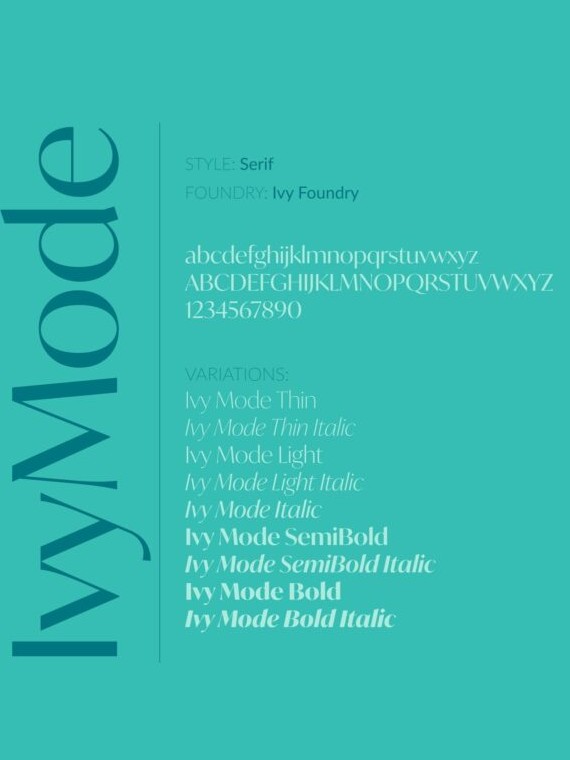
IvyMode là một bộ phông chữ thuộc dòng Sans-serif có độ tương phản cao, mang lại vẻ đẹp sang trọng, thanh lịch và đậm chất thời thượng. Với cấu trúc chữ sắc sảo và phong cách Flare Serif (những đường loe nhẹ ở đầu ký tự), việc sử dụng font IvyMode Việt hóa giúp các bản vẽ phối cảnh, hồ sơ năng lực hay bộ nhận diện thương hiệu công trình toát lên gu thẩm mỹ đẳng cấp.
Đặc điểm thẩm mỹ và phong cách của dòng font IvyMode Việt hóa
Nét lôi cuốn đặc trưng của font IvyMode nằm ở sự kết hợp tinh tế giữa tính hiện đại của phông chữ không chân và sự quý phái của các dòng Serif kinh điển. Cấu trúc ký tự sở hữu những nét thanh nét đậm rõ rệt, tạo nên nhịp điệu thị giác lôi cuốn và chiều sâu cho văn bản. Phiên bản font IvyMode Việt hóa đã được xử lý bảng mã Unicode kỹ lưỡng, đảm bảo các dấu thanh tiếng Việt được đặt ở vị trí cân đối, không làm phá vỡ cấu trúc thanh mảnh và sắc sảo của bộ chữ gốc.
Sự ổn định của bộ phông này còn thể hiện qua khả năng định hình phong cách cho các dự án kiến trúc cao cấp. Dù xuất hiện trên tiêu đề các bản thuyết minh dự án hay in ấn trên vật liệu kim loại, mica gương, IvyMode luôn duy trì được sự minh bạch và vẻ đẹp thời thượng. Đây là phương án hiệu quả để truyền tải các thông điệp về sự tinh tế, tính độc bản và tư duy thẩm mỹ nghệ thuật cho các công trình homestay, resort hay văn phòng container hiện đại.
| Phân loại phong cách | High-contrast Sans / Flare Serif / Modern |
| Mục đích phù hợp | Tiêu đề sang trọng, Logo, Profile kiến trúc |
Tư vấn trình bày: IvyMode phát huy hiệu quả thị giác cao khi bạn sử dụng cho các tiêu đề chính hoặc các đoạn trích dẫn ngắn. Do có độ tương phản nét chữ lớn, bạn nên phối hợp nó cùng một phông chữ không chân tối giản cho phần nội dung chi tiết để tạo sự cân bằng và dễ đọc cho bản thiết kế.
03 Ứng dụng phông chữ IvyMode vào thực tế công trình
Nhờ diện mạo giàu tính nghệ thuật và sang trọng, bộ phông chữ này mang lại giá trị thực tế cao trong khâu trang trí và quảng bá các dự án kiến trúc:
- Hệ thống nhận diện cho Boutique Homestay & Resort: Những nét chữ sắc sảo của IvyMode rất ăn ý khi xuất hiện trên biển hiệu bằng inox vàng gương hoặc đá tự nhiên. Font chữ này giúp không gian nghỉ dưỡng toát lên vẻ cao cấp và chuyên nghiệp ngay từ cái nhìn đầu tiên.
- Thiết kế hồ sơ năng lực dự án: Sử dụng font IvyMode Việt hóa cho tên dự án và các tiêu đề trang mục giúp hồ sơ của bạn trông chỉn chu như một tạp chí thời trang kiến trúc, tạo ấn tượng mạnh mẽ với chủ đầu tư.
- Trang trí không gian nội thất hiện đại: Bạn có thể dùng font này để cắt chữ nổi hoặc in tranh decor tại sảnh đón khách, phòng họp văn phòng container nhằm tạo điểm nhấn thanh lịch và thể hiện cá tính riêng của không gian làm việc.
03 Lưu ý kỹ thuật để bố cục font IvyMode Việt hóa chỉn chu
Để khai thác hiệu quả vẻ đẹp của dòng font đặc thù này mà không làm rối mắt người xem, người thiết kế nên lưu tâm một số kinh nghiệm sau:
- Kiểm soát kích thước hiển thị: Do có những nét thanh cực kỳ mảnh, IvyMode hiển thị đẹp ở kích thước trung bình đến lớn. Ở kích thước quá nhỏ, các chi tiết nét thanh có thể bị mờ nhòe, gây khó khăn cho việc quan sát từ xa.
- Nới rộng khoảng cách dòng: Với cấu trúc chữ mang tính trang trí cao, bạn nên để khoảng cách dòng thoáng một chút để các ký tự và dấu tiếng Việt không bị chồng lấn, giữ được sự minh bạch cho văn bản.
- Lựa chọn nền màu đơn giản: Phông chữ này đạt hiệu quả thẩm mỹ cao khi đặt trên các nền màu đơn sắc hoặc hình ảnh phối cảnh kiến trúc có ít chi tiết gây nhiễu, giúp các đường nét Flare Serif được tôn vinh rõ ràng.